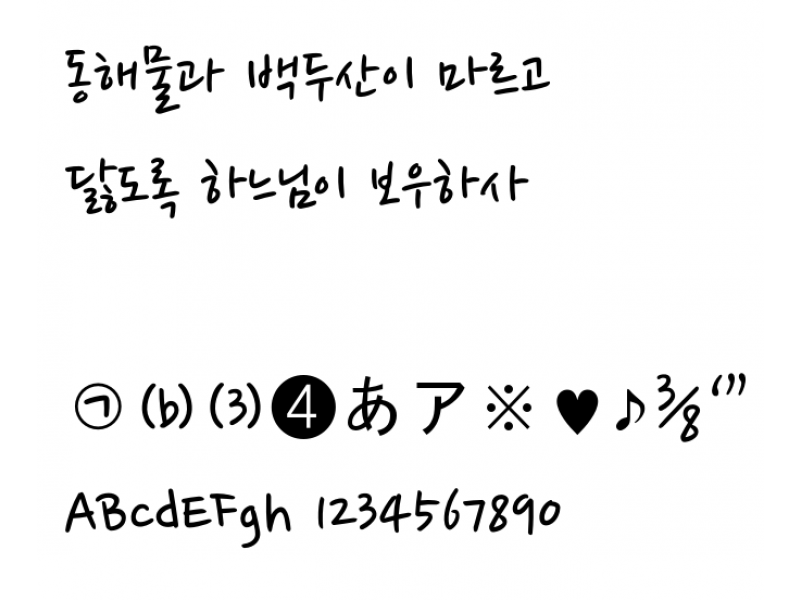
나눔손글씨 펜체는 깔끔한 선 처리와 생동감이 돋보인다. 반면 나눔손글씨 붓체는 꾸미지 않은 편안함과 리듬감이 매력적이다.
2009년 ‘손글씨 공모전’에 응모한 3만 3천 작품 중 대상작으로 뽑힌 정재경 님의 작품을 나눔손글씨체로 개발했다. 나눔 손글씨 붓체, 펜체 / 한글 2,350자, 영어 94자, KS약물 986자를 제공한다.